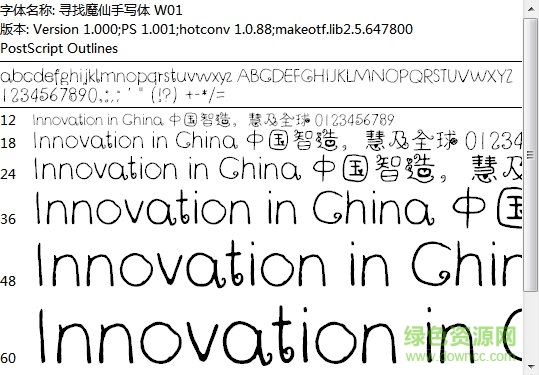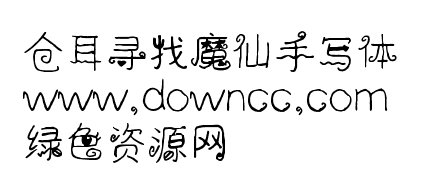
尋找魔仙手寫體是蒼耳字庫首款擁有魔法點(diǎn)綴的手寫體,讓文字變得有魅力起來,趣味的造型設(shè)計(jì)充滿了魔術(shù)氣息,給人童話般的美好體驗(yàn),綠色資源網(wǎng)獨(dú)家推薦!
尋找魔仙手寫體適合于兒童童話故事內(nèi)容的修飾,文字造型上打破了常規(guī)的端正,各種點(diǎn)綴和裝飾帶領(lǐng)大家走進(jìn)魔法的世界,很有活力哦!